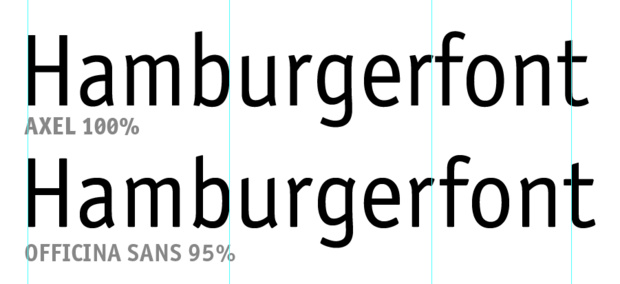
Officina Sans in schmal?
diese 19€ waren wirklich gut investitiert. Wobei mit der "Null" gibt es immer wieder Diskussionen auf der Baustelle (CAD-Pläne). Hat es Sinn bei FontShop nach der alternativen Null nachzufragen?
Du warst bestimmt nur verwirrt, weil hier jetzt soviel OT-Geplauder angesagt ist. Aber die Axel ist nicht OT, die ist on topic.
Lach, ja, da hast Du vermutlich recht! ;-)
diese 19€ waren wirklich gut investitiert. Wobei mit der "Null" gibt es immer wieder Diskussionen auf der Baustelle (CAD-Pläne). Hat es Sinn bei FontShop nach der alternativen Null nachzufragen?
Praktisch wäre eine alternative Null ja schon … Die mit dem Strich sähe in meiner Speisekarte schon seltsam aus. Wobei ich den Preis zur Not auch aus der Officina setzen könnte. Hmmm, ob Nachfragen hilft? Keine Ahnung, einfach mal ausprobieren.
axel ist aber definitiv nicht der schmallaufende schnitt der officina. :tutor:
es gibt da doch schon einige unterschiede, der größte ist sicherlich, dass die officina an allen ecken abgerundet ist und axel nicht. ich hätte die officina eher auf 95 % gesetzt, zumal diese auch besser ausgebaut ist.
Echt? Interessant! Hmmm, ich verwende eigentlich immer alle Schriften ganz artig in 100 % …
Ich habe für meinen Einsatzzweck keine wirklichen Bedenken, Officina und Axel zu kombinieren, da in 9 Punkt Schriftgröße die Unterschiede nicht wirklich ins Auge fallen dürften. Und die Axel ist der Officina sicherlich ähnlicher als irgendeine andere Schrift, die ich an ihrer statt verwenden könnte.
Echt? Interessant! Hmmm, ich verwende eigentlich immer alle Schriften ganz artig in 100 % …
Ich habe für meinen Einsatzzweck keine wirklichen Bedenken, Officina und Axel zu kombinieren, da in 9 Punkt Schriftgröße die Unterschiede nicht wirklich ins Auge fallen dürften. Und die Axel ist der Officina sicherlich ähnlicher als irgendeine andere Schrift, die ich an ihrer statt verwenden könnte.
ich finde es gut, dass du bei 100 % bleibst.
ich würde bei officina bleiben und es in 8,5 pt setzten, mit der schrift kann man das ruhig machen, lieber ein punkt kleiner als zu enge schrift nehmen.
Echt? Interessant! Hmmm, ich verwende eigentlich immer alle Schriften ganz artig in 100 % …
Wenn man es nicht übertreibt … 95 % sind in den meisten Fällen sicherlich nicht das Ende des Abendlandes. Und bei der Officina mit ihren großen Buchstabenabständen hat man noch ein zusätzliches Schräubli, an dem man drehen kann. Setz mal die Officina testweise auf 95% und die Buchstabenabstände auf Minus 2 Hundertstel. Es ergibt sich eine gigantische Platzersparnis und das Ergebnis ist in meinen Augen passabel. Es stellt sich auch die Frage, ob diese »Bastelei« nicht läßlicher* ist als die Bastelei mit den Officina-Ziffern in der Axel.
Hmmm, jetzt habe ich die Qual der Wahl!
Ich werde beides setzen und Pomeranz fragen, ob er so nett wäre, mir das zusätzlich noch in der Axel zu zeigen. Dann können wir hier mal vergleichen.
das stimmt.
wollte nur sichergehen das keiner mal später herausließt, dass axel der verlorene schmale sohn der officina ist. axel wurde für andere zwecke geboren.
normalerweise setzte ich fonts auch immer auf 100 %. aber es gibt fälle wo ein 95 % viel hilft und dem betrachter nicht ins auge fällt. ähnlich ist das mit laufweite auf -10. gerade die officina ist ja eher größzügig gekernt, da kann man das schonmal machen.
hier ein beipsiel zwischen axel 100% und officina auf 95%.
Bearbeitet ( von RobertMichael)
pachulski war eher, mir ist kundschaft dazwischen gekommen.
Ach toll, danke für Deine Hilfe. Hm, in der Tat, das kann man machen. Zumal die Officina sogar besser läuft … Ich werde das ausprobieren. Dann hätte ich auch das Problem mit der Null nicht.
:-)
genau, das problem mit der null umgehst du und auch andere sonderzeichen die axel nicht mitliefert. wobei ich die null vom axel ja mag, aber ich kann mir vorstellen das diese im fließtext störend wirkt. dafür ist axel aber wie gesagt nicht unbedingt geboren. der ist mehr so der tabellen-/zahlenschuft. (schuft — auch so ein wort welches ausgestorben ist)
typografski hat aber auch recht, officina ist ein arbeitspferd, die ist auch in kleineren graden noch sehr gut lesbar. nur in diesem fall merkt man ihr die schmalere tailie nicht an, ich würde fast behaupten das selbst erik das nicht mitbekommt ;)
Da hast du recht, es stört wirklich nicht, die einen Hauch schmaler zu machen.
Das mit der Null fände ich in der Tat unschön – das ist man in Speisekarten ja eher nicht gewöhnt.
Die Officina lässt sich wirklich gut verarbeiten, wobei ich da kürzlich auf deutliche Unterschiede gestoßen bin. Ich arbeite eigentlich mit der guten alten ITC Officina Sans (PS), die ich mal in einem Linotype-Paket mit gekauft hatte. Nun brauchte ich sie aber vor einer Weile in Russisch – also habe ich zusätzlich die OTF-Variante Multilingual gekauft, die neben der russischen Variante eben auch die normale deutsche beinhaltet.
Wie immer hängt der Wert der noch geht von der Schrift ab ... je höher der Kontast zwischen Horizontaler und Vertikaler ist, und je "eckiger" die Rundungen, desto mehr kann man der Schrift zumuten (wenn keine direkte Vergleichsmöglichkeit zur normalen Weite gegeben ist).
Oder in Schriften ausgedrückt: eine Swift Bold kann man kneten fast wie man will - eine Avantgarde Light eher gar nicht.